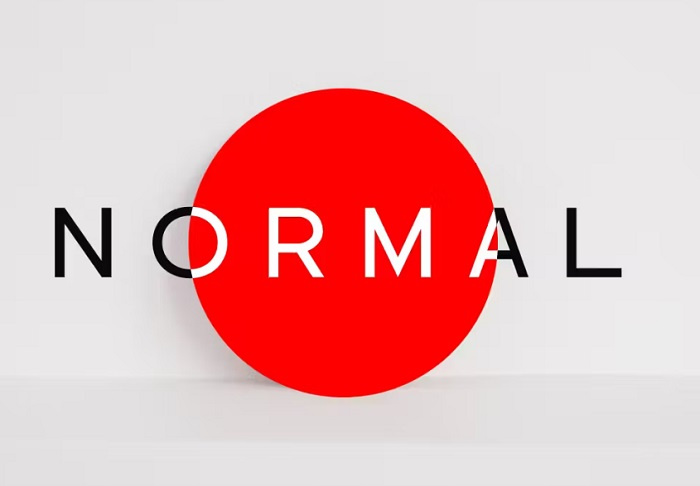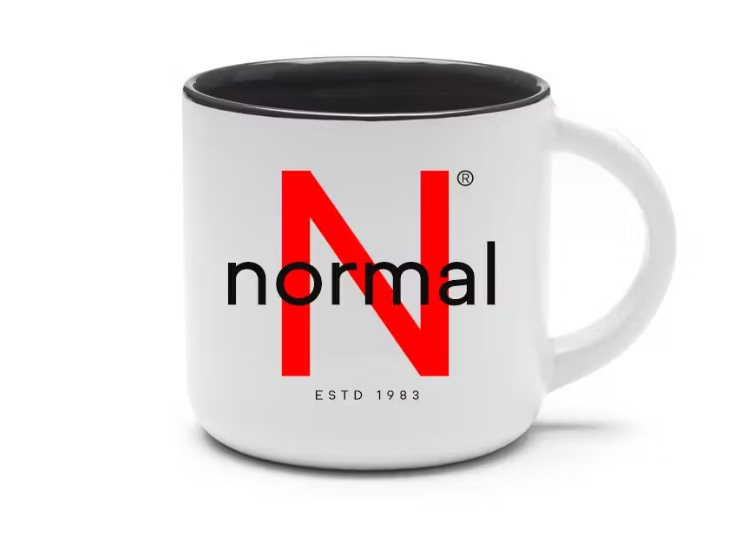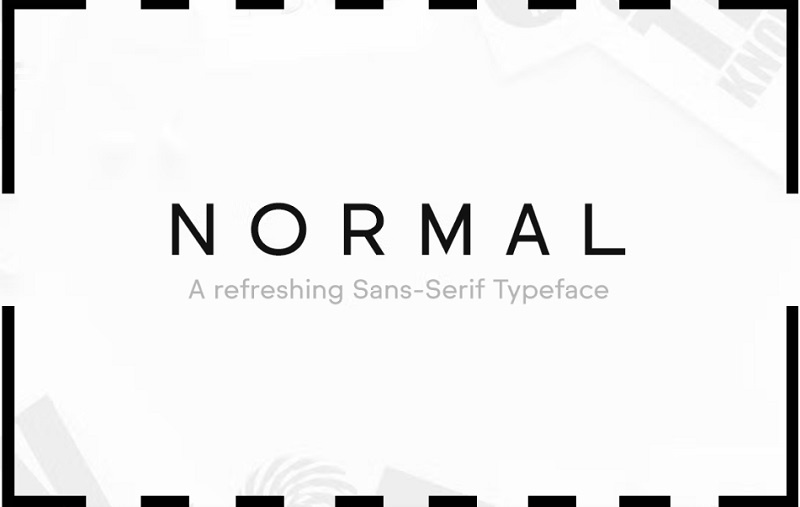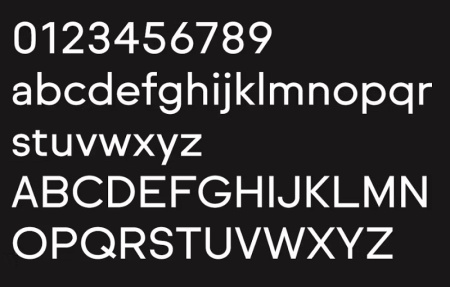
دانلود رایگان فونت انگلیسی معمولی NORMAL
دانلود رایگان فونت انگلیسی معمولی شامل حروف و کاراکتر های خالص و مینیمال با جذابیت خاص می باشد. این فونت انگلیسی به صورت کاملا رایگان از سایت gfx در اختیار شما قرار داده شده است. می توانید از آن برای لوگوتایپ ها، سرفصل ها، برندسازی، هویت های شرکتی، وب و چاپ و ... استفاده کنید. این بسته حاوی OTF، TTF و فونت های وب (همه EOT، SVG، TTF، WOFF است).
✅ دارای 5 حالت : Extra Light / Regular / Bold / ExtraBold